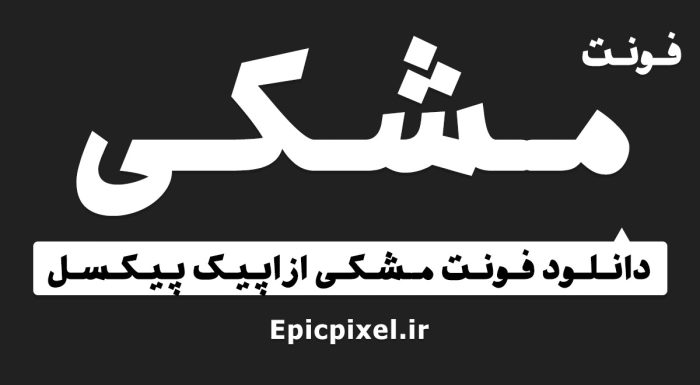
فونت مشکی فارسی
قدرت سادگی درخشش با فونت مشکی
فونت مشکی، علیرغم سادگی ظاهری، یک عنصر قدرتمند در طراحی گرافیک است. در دنیای رنگارنگ فونتها، مشکی باوقار و همهکاره خودنمایی میکند و پیامهای بصری را با شفافیت و تأثیرگذاری به مخاطب منتقل میکند. در این مقاله، به بررسی جایگاه فونت مشکی در طراحی گرافیک، مزایای استفاده از آن و نکات کاربردی برای به کارگیری مؤثر این عنصر ظریف اما تاثیرگذار میپردازیم.
فونت مشکی نماد وقار و خوانایی
رنگ مشکی به طور ذاتی با جدیت، قدرت و حرفهای بودن مرتبط است. استفاده از فونت مشکی در طراحیهای گرافیکی، به مخاطب احساس اعتماد و اطمینان القا میکند. این فونت همچنین خوانایی بالای متن را تضمین میکند و محتوا را به راحتی در اختیار مخاطب قرار میدهد. به همین دلیل، فونت مشکی برای طراحی وبسایتها، اسناد اداری، بروشورهای تبلیغاتی و هر جایی که خوانایی و انتقال واضح پیام اهمیت دارد، ایدهآل است.
تایپفیس مشکی در یک وزن سنگین برای مصرف کلمات و عناوین کوتاه طراحی شده است.
مزایای استفاده از فونت مشکی در طراحی گرافیک
استفاده از فونت مشکی در طراحی گرافیک، مزایای متعددی به همراه دارد:
- خوانایی بالا: همانطور که اشاره شد، مشکی تضاد بالایی با پسزمینههای روشن ایجاد میکند و خواندن متن را برای مخاطب آسان میکند. این ویژگی به خصوص برای مخاطبان با مشکلات بینایی یا در شرایط نوری ضعیف، بسیار حائز اهمیت است.
- حرفهای بودن: القا کننده حس جدیت و حرفهای بودن است. استفاده از فونت مشکی در طراحیهای گرافیکی، به کسب و کار شما وجههای معتبر و قابل اعتماد میبخشد.
- کاربردی بودن: به دلیل ماهیت خنثی خود، با هر رنگ و تصویری به خوبی ترکیب میشود. این ویژگی به طراحان اجازه میدهد تا با آزادی عمل بیشتری به چیدمان و ترکیب عناصر بصری بپردازند.
- جلب توجه: با وجود سادگی، فونت مشکی میتواند به طرز مؤثری در جلب توجه مخاطب نقش ایفا کند. طراحان گرافیک میتوانند با استفاده از این فونت درشت یا با طراحیهای خاص، بر روی بخشهای مهم متن تأکید کنند.
دانلودکاربردهای متنوع فونت مشکی در طراحی گرافیک
فونت مشکی کاربردهای گستردهای در طراحی گرافیک دارد. در اینجا به چند نمونه از این کاربردها اشاره میکنیم:
- طراحی وبسایت: برای متن اصلی وبسایتها، منوها و عناوین ایدهآل است. خوانایی بالای این رنگ، تجربه کاربری بهتری را برای مخاطبان رقم میزند.
- طراحی لوگو: لوگوهای مینیمالیستی و تک رنگ که از فونت مشکی بهره میگیرند، میتوانند بسیار تأثیرگذار و ماندگار باشند. سادگی و خوانایی این لوگوها باعث میشود تا به راحتی در ذهن مخاطب حک شوند.
- طراحی بروشور و پوستر: در طراحی بروشورها و پوسترهای تبلیغاتی، فونت مشکی میتواند برای برجسته کردن عناوین و بخشهای کلیدی مورد استفاده قرار گیرد. کنتراست بالای این رنگ، توجه مخاطب را به خود جلب میکند.
- اینفوگرافیک: در اینفوگرافیکها که هدف انتقال حجم بالایی از اطلاعات در فضایی محدود است، فونت مشکی به دلیل خوانایی بالا، انتخابی ایدهآل برای نمایش متن به شمار میرود.
- ایمیل مارکتینگ: در ایمیلهای تبلیغاتی، استفاده از فونت مشکی برای متن اصلی و عناوین، باعث حرفهایتر به نظر رسیدن ایمیل و افزایش نرخ کلیک بر روی لینکها میشود.
نکاتی برای استفاده مؤثر از فونت مشکی
برای استفاده مؤثر از فونت مشکی در طراحی گرافیک، به نکات زیر توجه کنید:
انتخاب فونت مناسب: فونتهای مختلف، شخصیتهای متفاوتی دارند. فونت انتخابی شما باید با ماهیت پروژه و پیامی که میخواهید منتقل کنید، همخوانی داشته باشد.
ایجاد سلسله مراتب بصری:
با استفاده از فونتهای مشکی با ضخامتهای مختلف، میتوانید سلسله مراتب بصری در طرح خود ایجاد کنید. برای مثال، از فونتهای ضخیمتر برای عناوین و فونتهای نازکتر برای متن اصلی استفاده کنید.
استفاده از فونتهای مکمل:
دانلودبرای ایجاد تنوع و جذابیت بیشتر، میتوانید از فونتهای رنگی یا طرحدار در کنار فونت مشکی استفاده کنید. فقط به خاطر داشته باشید که فونتهای مکمل باید با فونت مشکی همخوانی داشته باشند و خوانایی متن را تحت شعاع قرار ندهند.
توجه به فضای خالی:
فضای خالی اطراف متن، به خوانایی آن کمک میکند. از قرار دادن متنهای فشرده و بدون حاشیه خودداری کنید.
آزمایش و خطا:
بهترین راه برای یافتن بهترین ترکیب فونت مشکی در طراحی خود، آزمایش و خطا است. فونتهای مختلف را با هم امتحان کنید و ببینید کدام ترکیب بیشترین تأثیرگذاری را دارد.
سوالات متداول
1. چه زمانی باید از فونت مشکی در طراحی گرافیک استفاده کرد؟
استفاده از فونت مشکی در هر نوع طراحی گرافیکی که خوانایی، وضوح و حرفهای بودن در آن اهمیت دارد، ایدهآل است.
2. چگونه میتوان از فونت مشکی برای جلب توجه مخاطب استفاده کرد؟
میتوانید از فونتهای مشکی درشت، ضخیم یا با طراحیهای خاص برای برجسته کردن بخشهای مهم متن و جلب توجه مخاطب استفاده کنید.
3. آیا استفاده از فونت مشکی در طراحی گرافیک خستهکننده نیست؟
خیر، اگر از فونت مشکی به درستی استفاده شود، میتواند به جذابیت و تأثیرگذاری طراحی شما کمک کند. تنوع در ضخامت، ترکیب با فونتهای دیگر و استفاده از فضای خالی، از خستهکننده شدن طرح جلوگیری میکند.